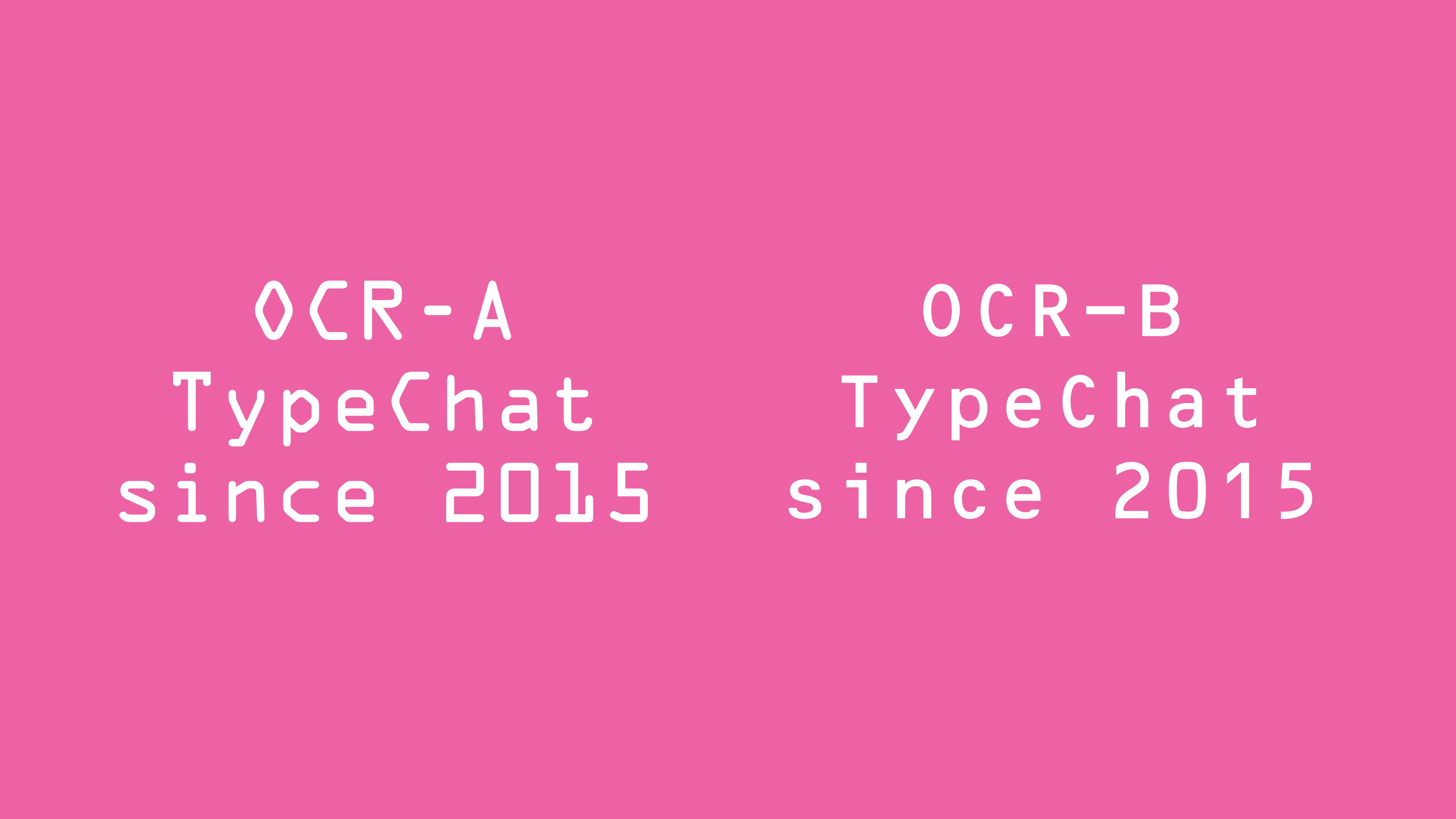
完整视频回顾:Brand Talks 2025 蒙纳字体与品牌论坛·深圳
7 月 25 日下午,蒙纳再次来到素有「设计之都」美誉的深圳,带来蒙纳字体与品牌论坛,一览品牌如何用字体悄然流露的气质与情绪,触动人心,连接彼此。
蒙纳传奇字体大师小林章亲临分享现场,携手蒙纳全球品牌创意总监 Graham Sturt,与多位深耕品牌、字体与视觉语言领域的杰出实践者,通过个人经历与典型案例,呈现他们如何以字体为载体,赋予品牌人文温度,启发更深层的联结与共感。
小林章
蒙纳字体创意总监
Type as visible “voice”
蒙纳字体创意总监小林章以「字体作为可见之声」为题,分享了字体如何承载情绪、语气与品牌个性。
他通过交通标志、「Love Story」字体演示等案例,展示了同一句话因字体不同而传达出截然不同的语气。字体不仅仅是传递信息,更是在向用户表达态度与情绪,树立关键作用。
在企业定制字体案例中,小林章讲述了与索尼、阿里巴巴、马自达、朗格表等品牌的合作过程,强调字体如何在细节中体现出品牌的真实面貌。
从字母造型到标点位置,每一个微调都服务于品牌的视觉表达。而这正是字体设计师的核心价值:用字体,说出品牌真正想说的话。
Graham Sturt
蒙纳全球品牌创意总监
From pixels to people: The power of typography to humanize brands
蒙纳全球品牌创意总监 Graham Sturt 也是荷兰设计界的重要声音,他从平面设计的视角出发,探讨字体这一被长期低估的视觉主角。他表示,字体不是装饰,而是语言的外衣,是品牌的语气、性格和情感。
他分享了多个以字体为核心的案例,包括阿姆斯特丹创意园区的可变字标、赛车频道中运用多普勒效应的动感字体等,展示字体在传递理念与激发情感中的力量。
同时,他也指出在「同质化」的简洁设计趋势中,个性字体能帮助品牌脱颖而出。通过 Burberry、Heineken、NASA 副标等案例,Graham 提出:字体能建立信任、展现创意、增加亲和力,品牌应将字体作为战略资产,展现温度和辨识度。
梁佳
谢谢设计联合创办人与创意总监
字与城市|从街头到设计
谢谢设计联合创办人兼创意总监梁佳老师的演讲,围绕「字体与城市」的关系展开,充满人文温度与在地洞察。他分享了自己如何从逛街中汲取灵感,通过观察街头手写招牌与本地文化,将城市的烟火气融入字体设计。
他首先介绍了在广东南海大地艺术节的创作,从文心饼店的复古招牌到「太平」字样的街头主视觉,每一件作品都展现出他对街景、手工艺和人情味的融会贯通。
此外,他也讲述了为沪上阿姨打造新版品牌形象的幕后思考:融合旗袍、老上海广告美学与现代审美,打造年轻又具辨识度的视觉系统。
最后,他介绍了扎根东莞本土文化的腊肠主题项目,通过字型与装置设计结合,唤起对老城生活的共鸣。字体作为文化载体所具有的无限可能,帮助设计在真实生活中生根发芽。
刘庆
《字谈字畅》制作人兼主播 / TheType 编辑
人性化的字体排印
在这场关于「人性化的字体排印」的分享中,The Type 编辑、《字谈字畅》制作人兼主播主播刘庆带来了不少精彩观点。
他从一款「给机器读」的字体 OCR-B 讲起,设计师 Adrian Frutiger 坚持即使是机器用的字,也要为人考虑,读起来舒服。
从 OCR 字体的演进到「和平板」断词错误,从中文标点影响居中对齐,到语义换行的必要性,刘庆用真实案例提醒观众:字体排印的核心,是服务于人,而不是满足算法。
尤其在中文语境中,排版算法、视觉对齐、语义判断,还有很大的提升空间。“排得对不对,不是看代码,而是看你我读起来顺不顺。”
这是一场兼具专业性与人文关怀的演讲,也是一份写给设计师、开发者与内容创作者的提醒:再先进的技术,最终还是为人所用。
嘉宾对谈
本次对谈围绕 AI 时代下字体、人性与创造的边界展开,三位嘉宾从自身实践出发,深入探讨了 AI 在设计工作中的角色与边界。
OPPO 高级艺术指导杨宇晰分享了如何将 AI 作为高效的创意伙伴,拓宽设计可能性的同时保有人的判断力;前华为 Art Studio 美术指导陈诗祺强调 AI 虽提高效率,但真正能打动人心的,仍是设计师对品牌个性的理解与沉淀;谢谢设计创意总监梁佳则从街头文字的衰退谈起,呼吁在同质化浪潮中保留手工痕迹与视觉多样性。
三位嘉宾一致认为,AI 可为规范和速度服务,但无法取代创作中的人性与直觉。整场对谈融合了宏观洞察与微观感知,激发观众对未来设计生态的深层思考。
签约仪式
在论坛尾声,蒙纳字库与 IXDC 国际体验设计大会正式签署战略合作协议,标志着双方在字体与体验设计领域开启全新篇章。
IXDC 作为全球领先的用户体验创新平台,致力于连接设计、科技与商业实践。此次携手,意味着字体将以更具前瞻性的方式融入品牌与用户体验,激发创意潜能。
IXDC 秘书长张运彬先生与蒙纳字库华南业务负责人罗晓明先生分别进行了致辞,并签约战略合作协议,期待未来共创设计新价值。
结语
从品牌的可见之声,到城市街头的烟火字体;从人性化的排印判断,到 AI 技术带来的思维挑战。在这个信息与情感交汇的夏日下午,我们共同见证了字体如何不仅连接视觉与语言,更连接品牌与人,连接我们与这个真实世界的感知。